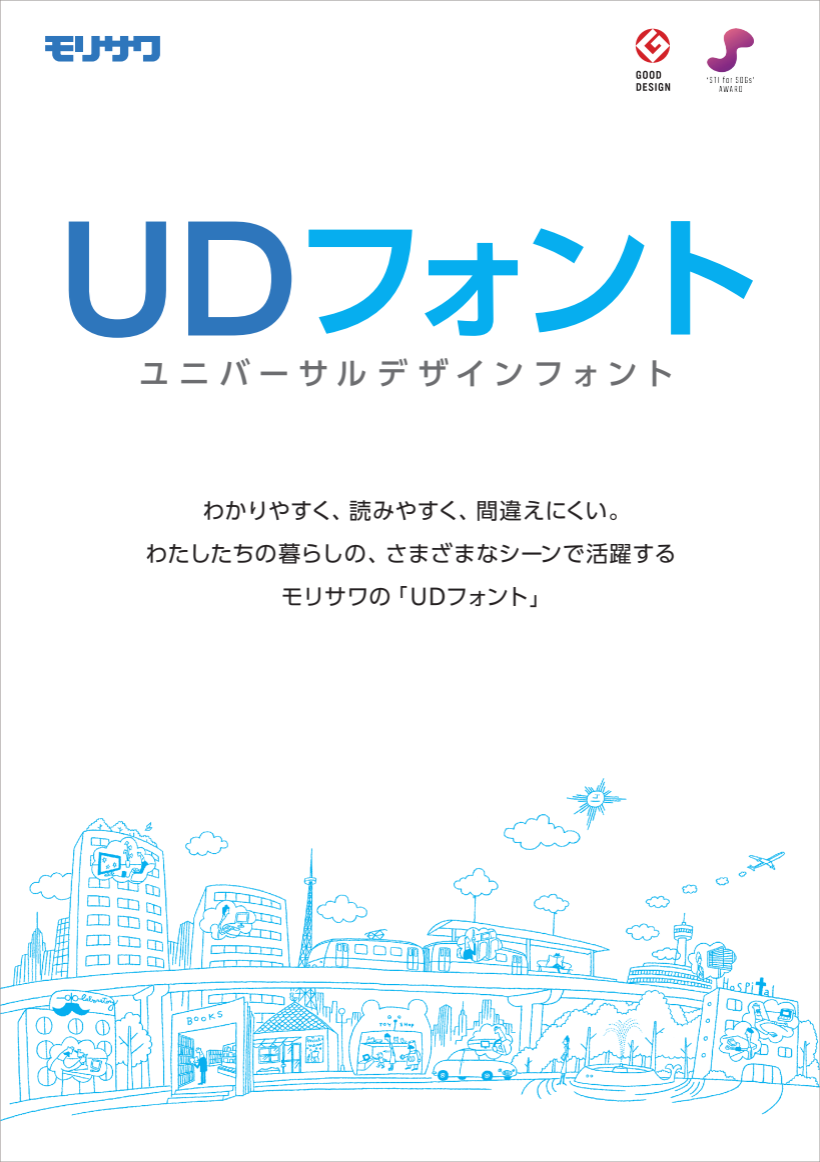
ユニバーサルデザインと
文字
私たちは情報の多くを視覚から得ています。
そして、その視覚情報のほとんどは、文字によってもたらされていることは、もはや疑いのないことでしょう。雑誌や書籍、新聞、広報誌といった印刷物はもちろん、Webやメール、携帯電話ですら文字なくしては成り立ちません。
ひとたびどこかに行こうと思えば、案内板や交通標識、手元の切符にいたるまで、私たちはそこに記録された文字情報を頼りに行動をしています。文字は私たちの日常に、ごく当たり前のように浸透しているのです。
ではその文字が読みにくかったとしたら、わかりにくかったとしたらどうでしょうか。「300円」なのか、「800円」なのかわからない。濁点と半濁点の判別ができない。細い文字がかすれて読めない……文字の不明瞭さは、時として致命的なコミュニケーションの欠如を引き起こします。
このような事態を未然に防ぐためには、文字そのものがわかりやすく、読みやすく、読み間違えにくいことが求められます。つまり、誰がどんな状況であっても、正しく機能する「ユニバーサルデザイン」という発想が、文字のデザインにおいても求められているのです。
- 文字のかたち
がわかりやすい - 文章が読みやすい
- 読み間違えにくい
ユニバーサルデザイン(UD)に対応した文字とはどのようなものなのでしょうか。そこには厳密な字形の定義があるわけではありません。だからこそ、フォントメーカーの、フォントデザイナーのUDに対する考えかたが重要になります。
モリサワUD書体は、「文字のかたちがわかりやすいこと」「文章が読みやすいこと」「読み間違えにくいこと」をコンセプトに開発されました。その過程では、“小サイズですべての文字が問題なく判別できること”をひとつの基準として、ベースとなる書体の各文字が見直され、繰り返しUD書体のコンセプトに適合しているかどうかを検証しました。
一方で、わかりやすさを重視するあまりに文字の美しさが損なわれることのないよう、視認性とデザイン性、双方のバランス調整がデザイナーの手によって施されました。
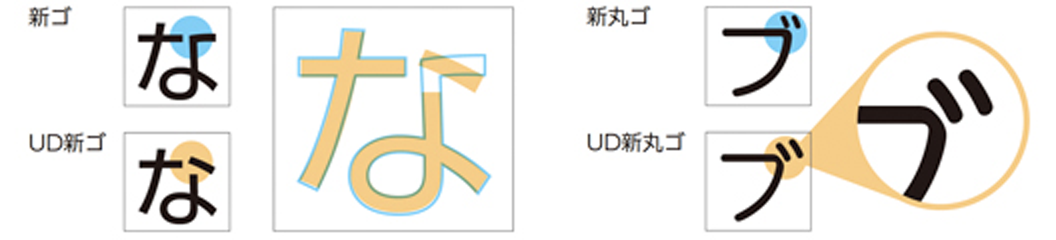
こうして、ユニバーサルデザインに対応した明朝体「UD黎ミン」、ゴシック体「UD新ゴ」「UD新ゴNT」、丸ゴシック体「UD新丸ゴ」の4種24書体が完成しました。
リュウミンに代表される、通常の明朝体は、横画が細く、縦画の幅によって、文字の太さを表現していました。この横画の細さは、明朝体らしい気品を醸し出す一方で、読む・見る環境によってはかすれてしまい、視認性が損なわれてしまうことがあります。
「UD黎ミン」は、このような問題に対処するために、横画を太くすることによって、あらゆる環境で高い視認性と可読性を実現しました。